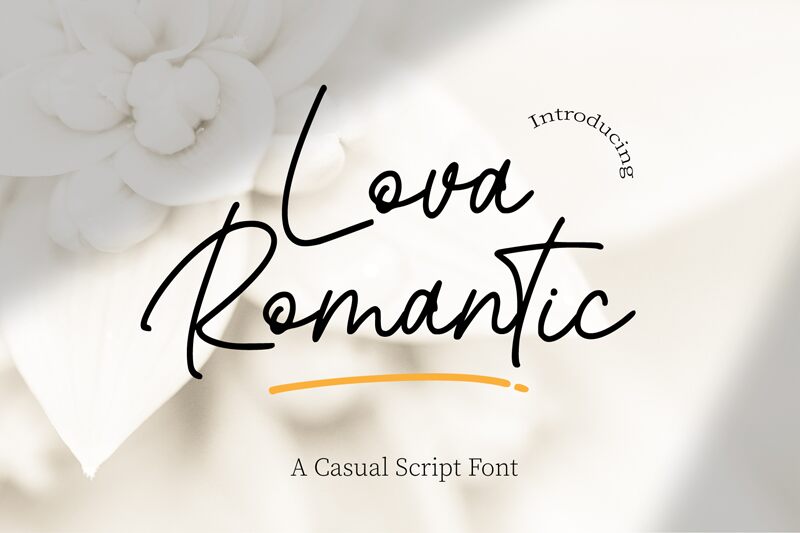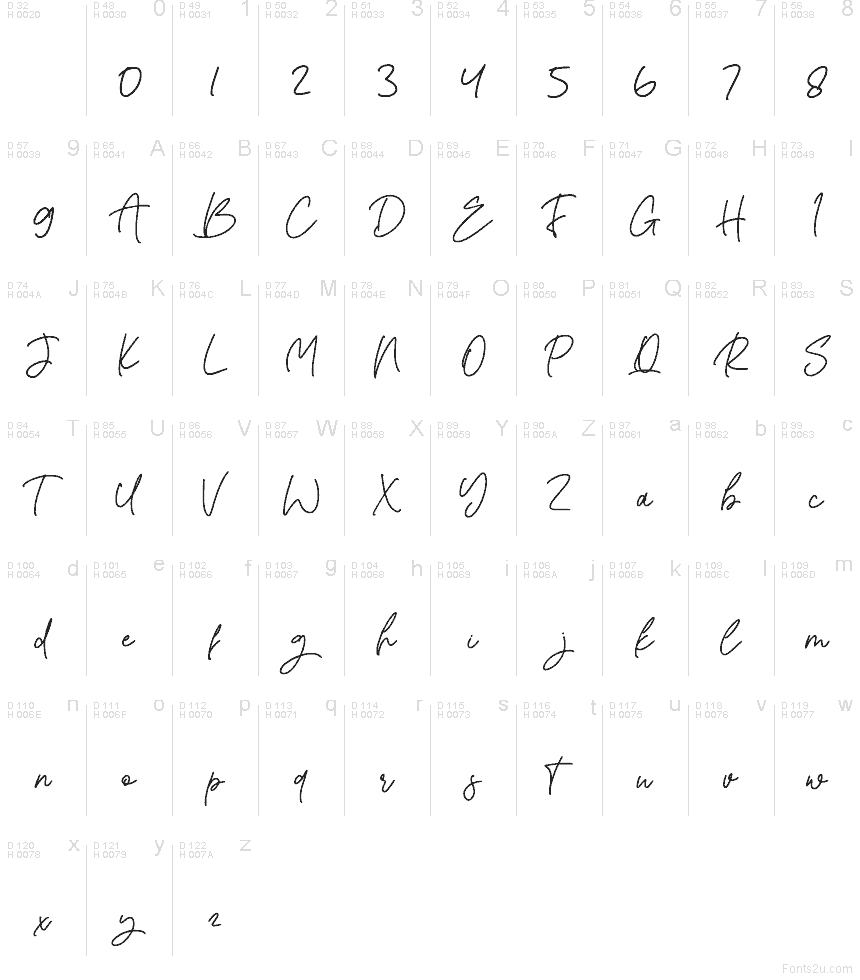
Lova Romantic di Aminmario è un font calligrafico gratuito caratterizzato da un tratto leggero e romantico, con un ritmo fluido e personale. Le lettere si muovono in linee lunghe e armoniose, con forme arrotondate e riccioli, completate da un'alta fioritura finale che dona al carattere l'aspetto di una firma veloce o di una nota scritta con affetto.
Si adatta perfettamente a partecipazioni di nozze, branding nel settore beauty, biglietti d'auguri, post sui social e packaging artigianale, dove un tocco umano e delicato conta più della rigida formalità. Essendo un font gratuito, funziona benissimo anche per titoli brevi, copertine e monogrammi, poiché i collegamenti ad anello e le estensioni permettono alle parole brevi di respirare.